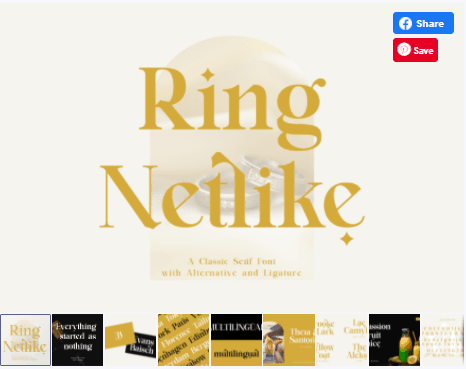
Ring Netlike Font
Ring Netlike - элегантный и аутентичный шрифт с засечками. Этот шрифт закодирован в кодировке PUA, что означает, что вы можете легко получить доступ ко всем глифам и штрихам!
Влюбитесь в его невероятно универсальный стиль и используйте его для создания впечатляющих дизайнов!